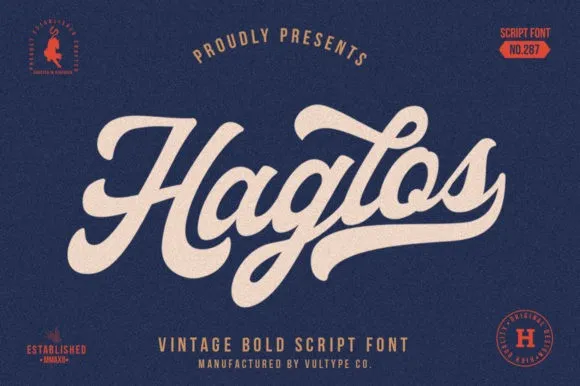
Haglos Bold Script Font – Download Grátis
Olá amantes do design! Introduzimos a Haglos Bold Script Font, uma nova opção entre as fontes de script vintage. Esta elegante e bem projetada é perfeita para seus projetos mais excepcionais. A Haglos Bold Script tem um estilo retro que se destaca em qualquer projeto. Ela é marcada por linhas aparentemente naturais, proporcionando a sensação quase que realística de escrever com sua própria caneta. Além disso, seu design permite alternativas contextualizadas, tornando-a perfeita para textos informais ou até mesmo para criar uma aparência manuscrita. Esta fonte é especialmente útil para projetos vintage, desde t-shirts e logotipos, até labels, badges, e até mesmo postagem de mídia social. Suas linhas são fortes, mas também suaves e perfeitamente legíveis – tudo isso feito com uma excelente combinação de terminais e ornamentos que permitem aos designers criar uma mistura elegante dos pares de letras. A Haglos Bold Script é certamente uma fonte que você não quer passar por cima ao procurar uma nova fonte para seu próximo projeto.
Designer: Tommy Soft